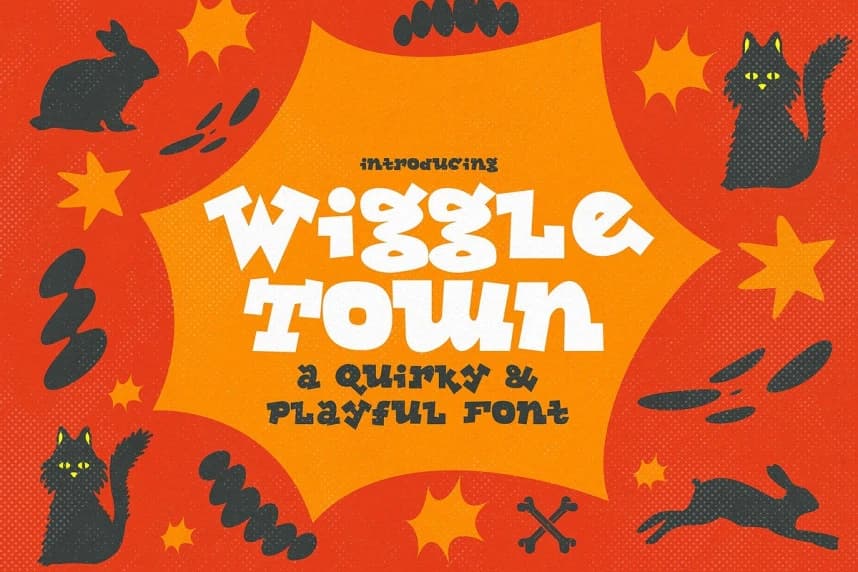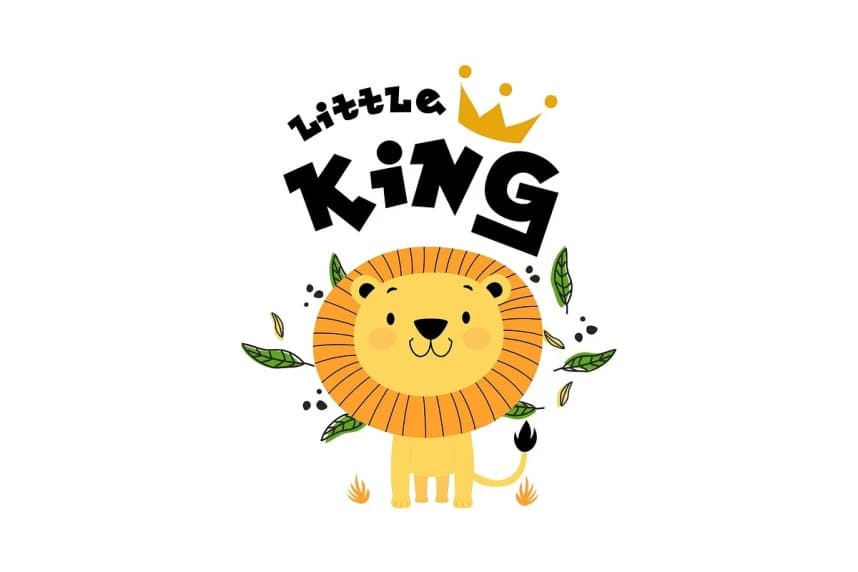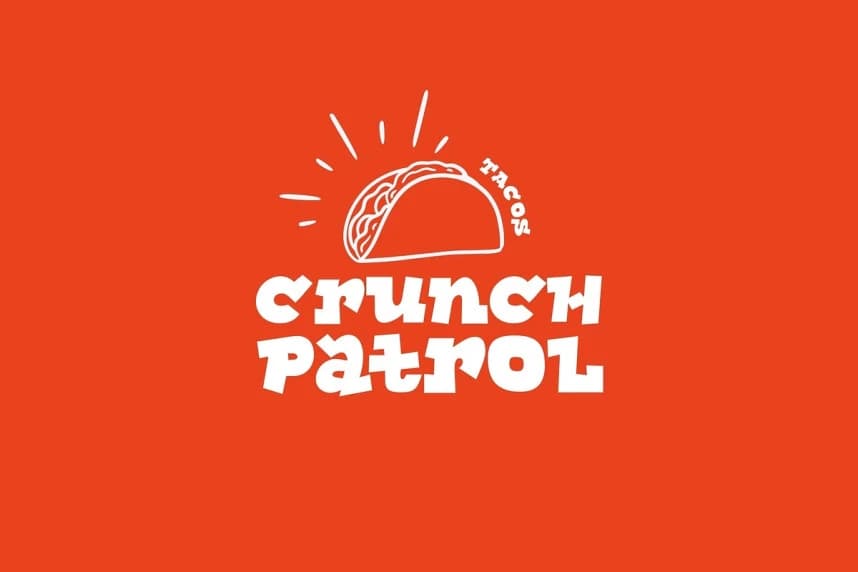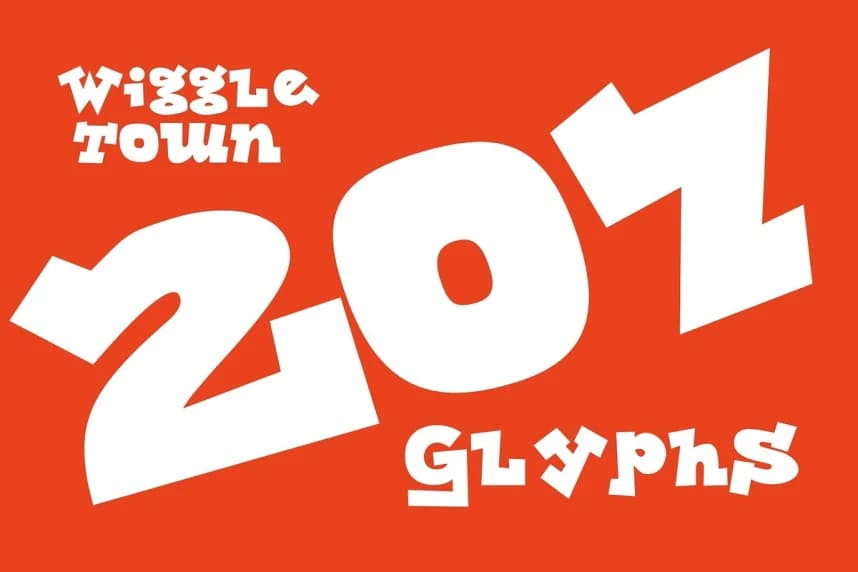
Wiggletown Playful Font
Wiggletown Playful Font, kişiliğiyle dolup taşan eğlenceli ve sıradışı bir yazı tipidir. Sayfada adeta dans eder gibi tasarlanmış bu neşeli font 207 benzersiz glif içerir ve 68 dili destekler; bu da onu ne kadar çok yönlü kılarsa o kadar canlı kılar.
Wiggletown Playful Font kişiliğiyle dolup taşan eğlenceli ve garip bir yazı tipidir. Sayfa boyunca adeta dans eder gibi tasarlandı; bu neşeli yazı tipi 207 benzersiz glife sahiptir ve 68 dili destekler, bu da onu ne kadar çok yönlü yapıyorsa o kadar da parlak ve canlı kılar.
Wiggletown Playful